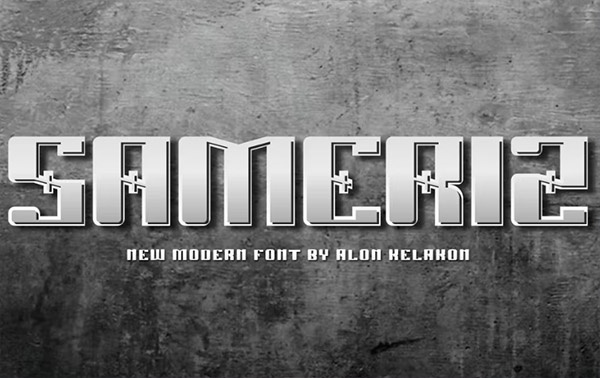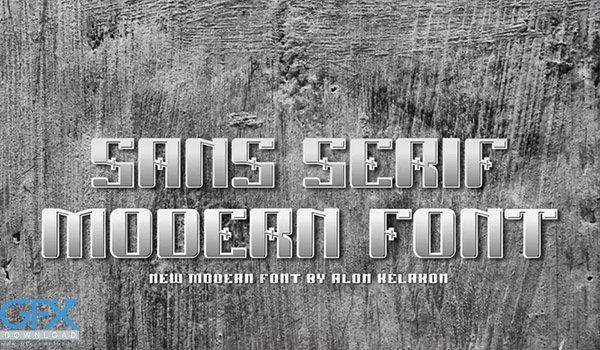
فونت سامریز یک فونت بی نظیر است. آماده استفاده برای طراحی شما مانند برچسب زدن، لباس، صحنه فیلم، پوستر، عنوان فیلم، کنسرت ها، جلد آلبوم، لوگو و موارد دیگر. برای دانلود رایگان فونت Sameriz از جی اف ایکس دانلود به ادامه مطلب مراجعه کنید.
• نام فونت: Sameriz